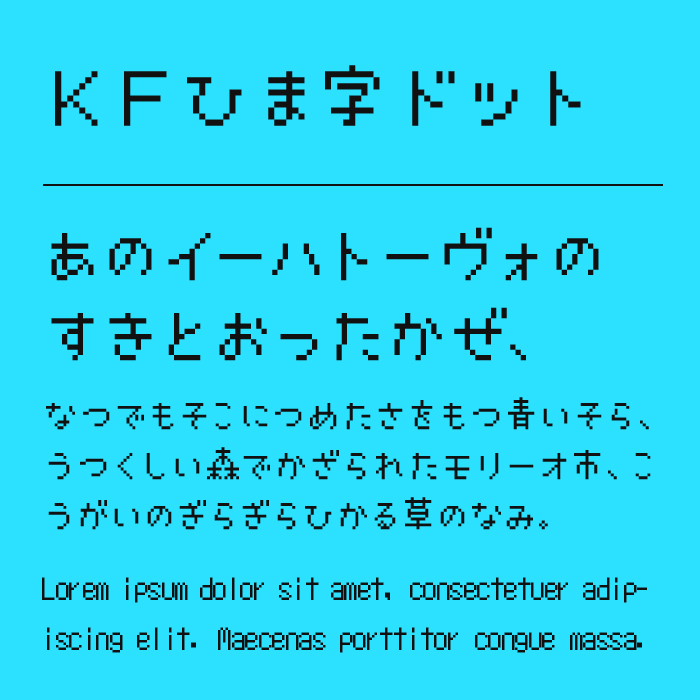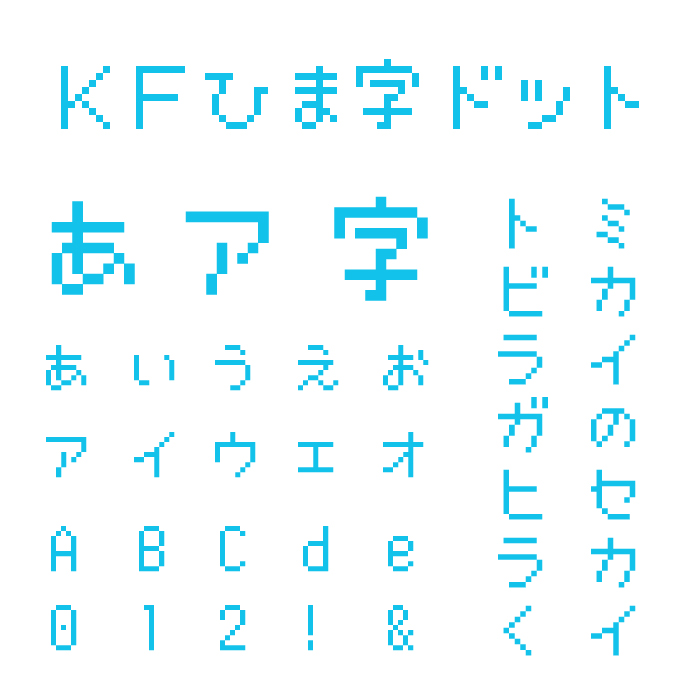
KFひま字ドット
KFひま字ドットフォントは、ピクセルで描いたようなドット調のフォントで、どこか懐かしさと丸みが愛らしさが感じられるピクセルフォントです。
丸みがあるピクセルが特徴的で、ゲームのレトロ感や80〜90年代風のビジュアル表現にぴったりなテイストを持っています。
デジタル感やユーモアを演出したい時に最適で、特にSNS用の画像、チラシ、同人誌系のタイトルなどでの使用に向いています。
フォントの文字見本
KFひま字ドット
収録文字は、漢字(小学1年生で習う80字+α)・ひらがな・カタカナ・アルファベット・数字・記号が収録。